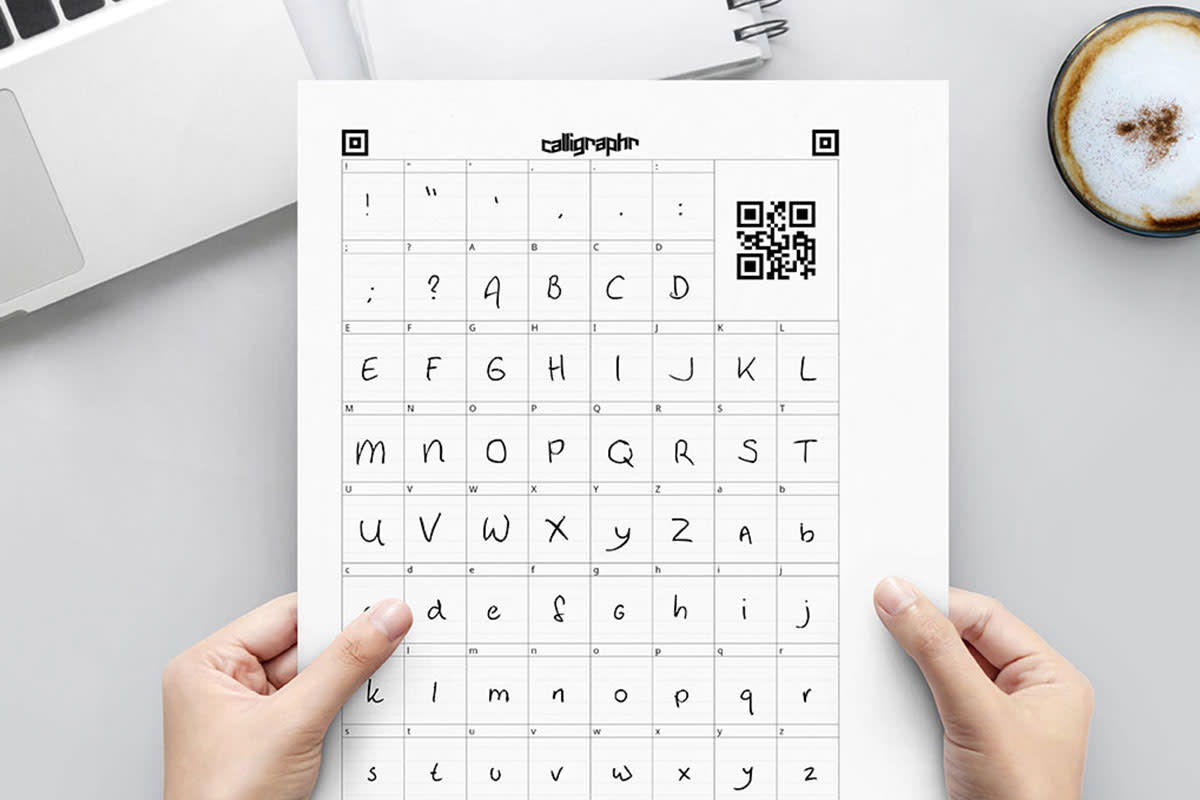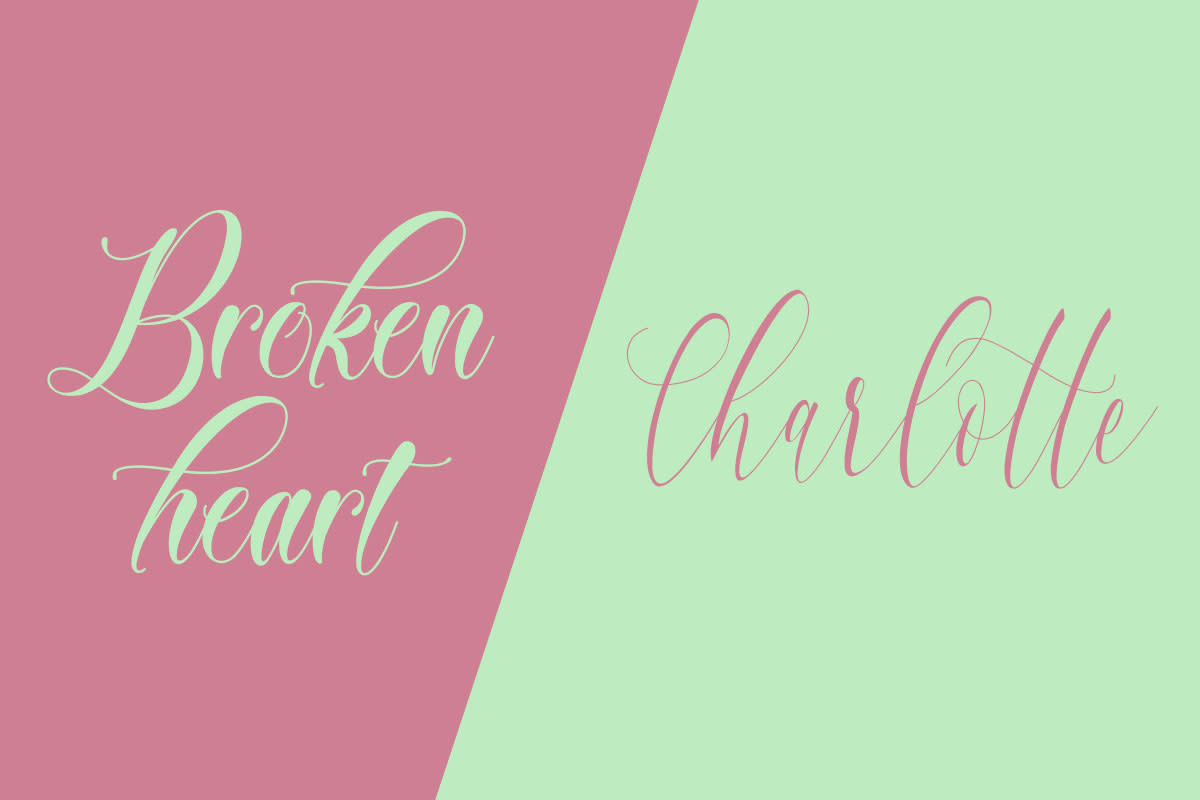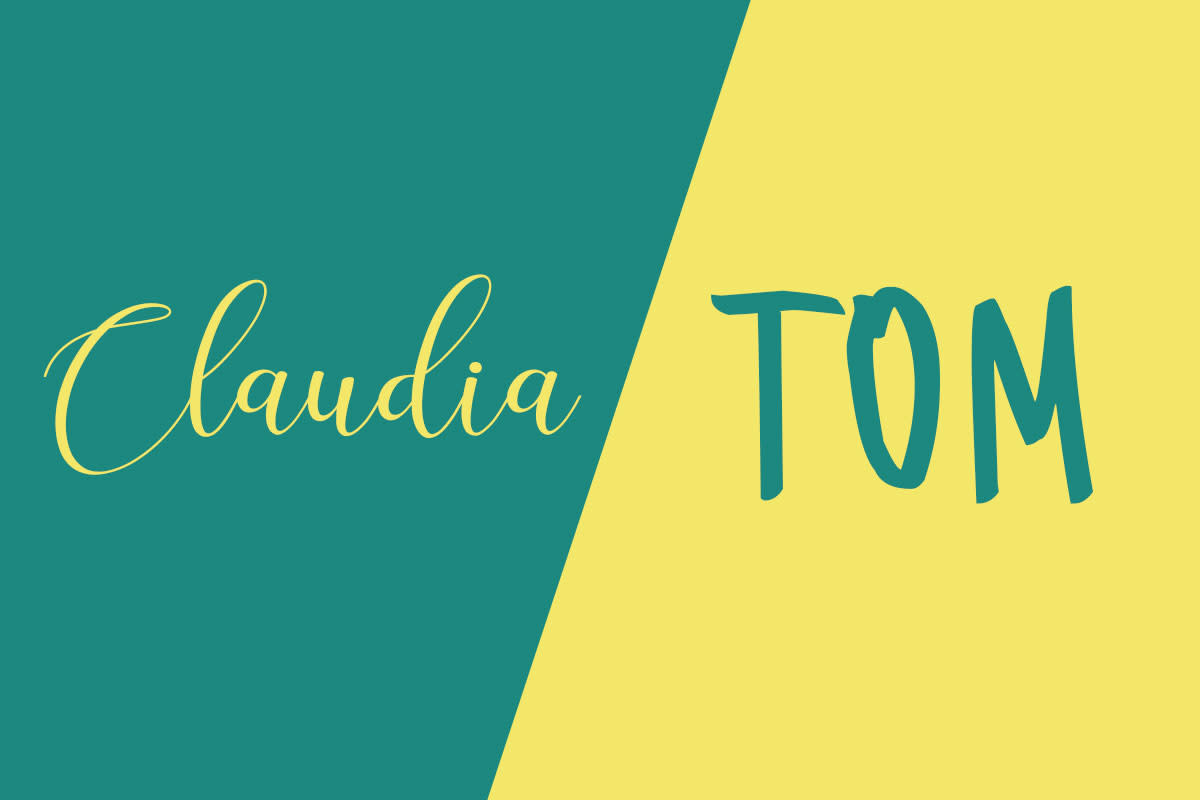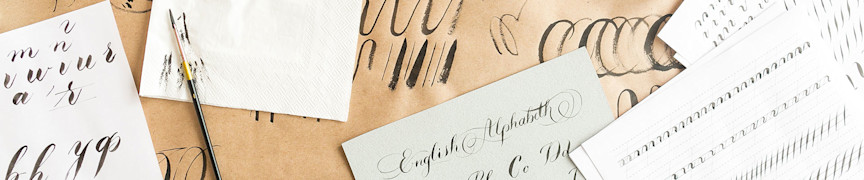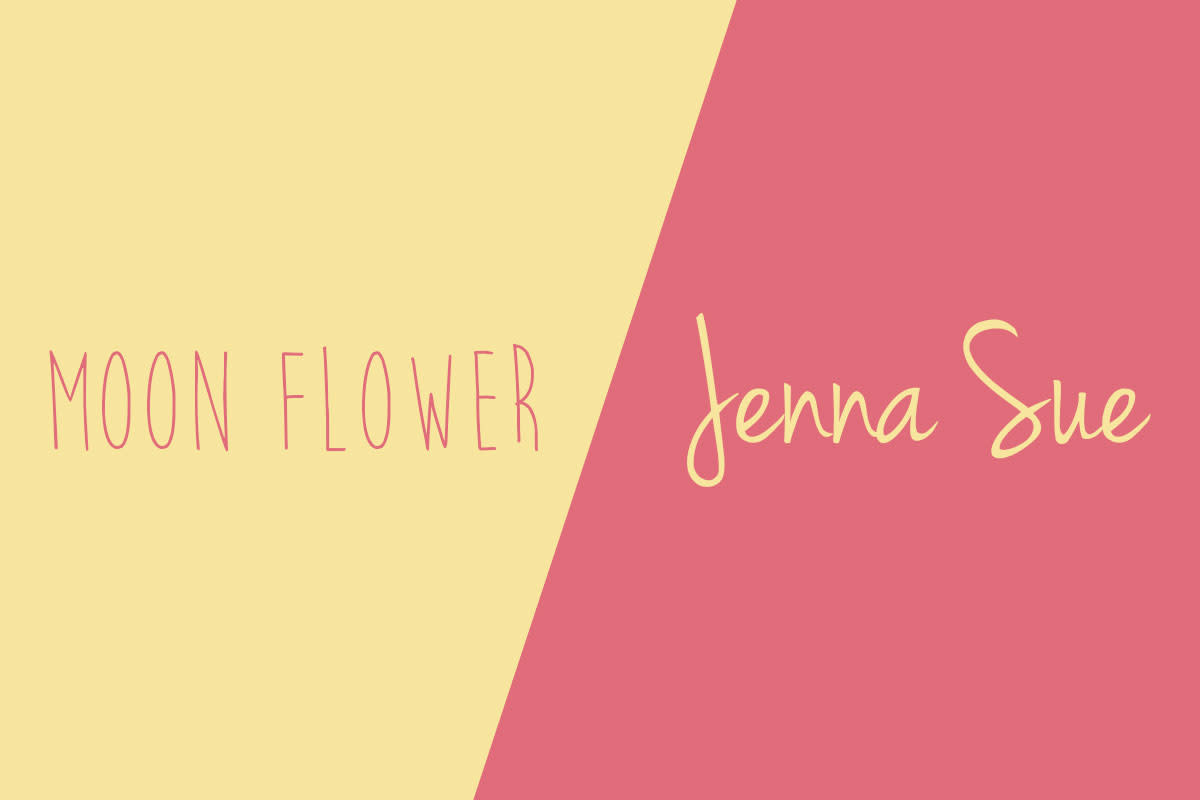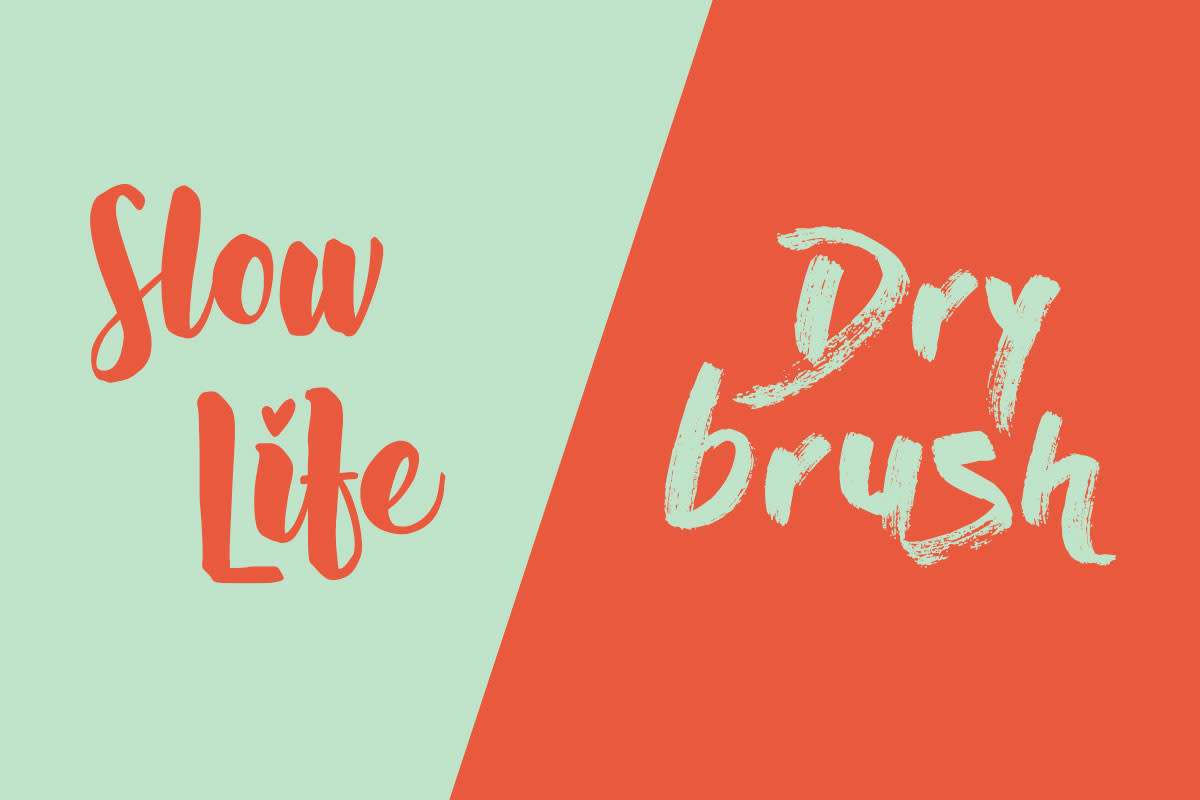
FreebieFriyay: alles over de mooiste handgeschreven fonts
Er zijn ontzettend veel verschillende soorten lettertypes. Van hele strakke moderne lettertypes tot lekkere old school-fonts. Voor elk design is een bijpassend font te vinden. Wil jij je ontwerp nou echt een persoonlijke touch geven? Dan is een handgeschreven font een goede keus. In dit blog vertel ik je meer over de verschillende handgeschreven fonts én laat ik je natuurlijk een aantal mooie voorbeelden zien.
Script font
Handgeschreven lettertypes vallen onder de categorie script fonts. Dit zijn lettertypes gemaakt uit geschreven letters die een losse sfeer aan je ontwerp geven. Script fonts kun je ook weer onderverdelen in verschillende soorten, zoals: handgeschreven lettertypes, maar ook de brushletters (alsof ze geschilderd zijn) en kalligrafieletters vallen onder script fonts. freebiefriyay-17-script
Handgeschreven fonts
Handgeschreven fonts zien eruit alsof ze, zoals de naam al doet vermoeden, handgeschreven zijn. Van kinderlijke handschriften tot doktershandschriften. Voor elk soort ontwerp is wel een lettertype te vinden. Handgeschreven lettertypes die ik erg mooi vind zijn Tomatoes, Moon Flower en Jenna Sue. freebiefriyay-17-handgeschreven
Brush letters
Brush fonts zien eruit alsof ze met een penseel gezet zijn. Vaak zijn deze letters wat dikker dan handgeschreven fonts, en brush letters zijn wat krullender. Waar handgeschreven fonts ook wel strak kunnen zijn, zijn de brush fonts dat niet. Brush fonts kun je bijvoorbeeld heel goed gebruiken in een retro ontwerp. Voorbeelden van brush lettertypes zijn Dry Brush, Slow Life en Chasing Embers. freebiefriyay-17-brush
Kalligrafie lettertypes
Kalligrafieletters zijn erg sierlijk, met veel krullen en heel geschikt voor ontwerpen die een chique uitstraling hebben. Ook worden kalligrafie fonts vaak gebruikt op bijvoorbeeld trouwkaarten. Ben je op zoek naar kalligrafie lettertypes? Dan zijn deze drie zeker aanraders: Broken Heart, Charlotte Calligraphy en Inkland freebiefriyay-17-kalligrafie
Een font van jouw handschrift
Wil je nou een echt persoonlijk ontwerp maken? Maak dan een lettertype van jouw eigen handschrift! Mijn collega Jeroen schreef hier een blog over. Hij laat je zien hoe makkelijk het is om van je eigen handschrift een font te maken. freebiefriyay-17-eigen-handschrift